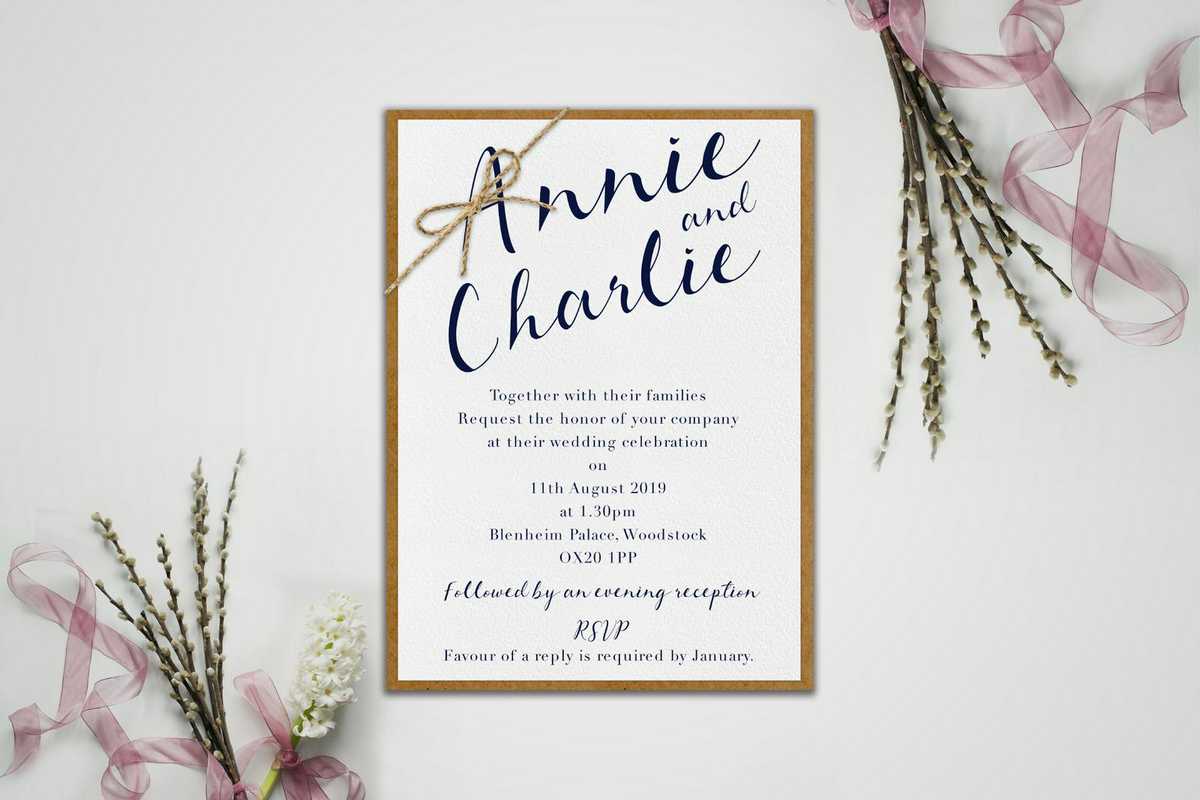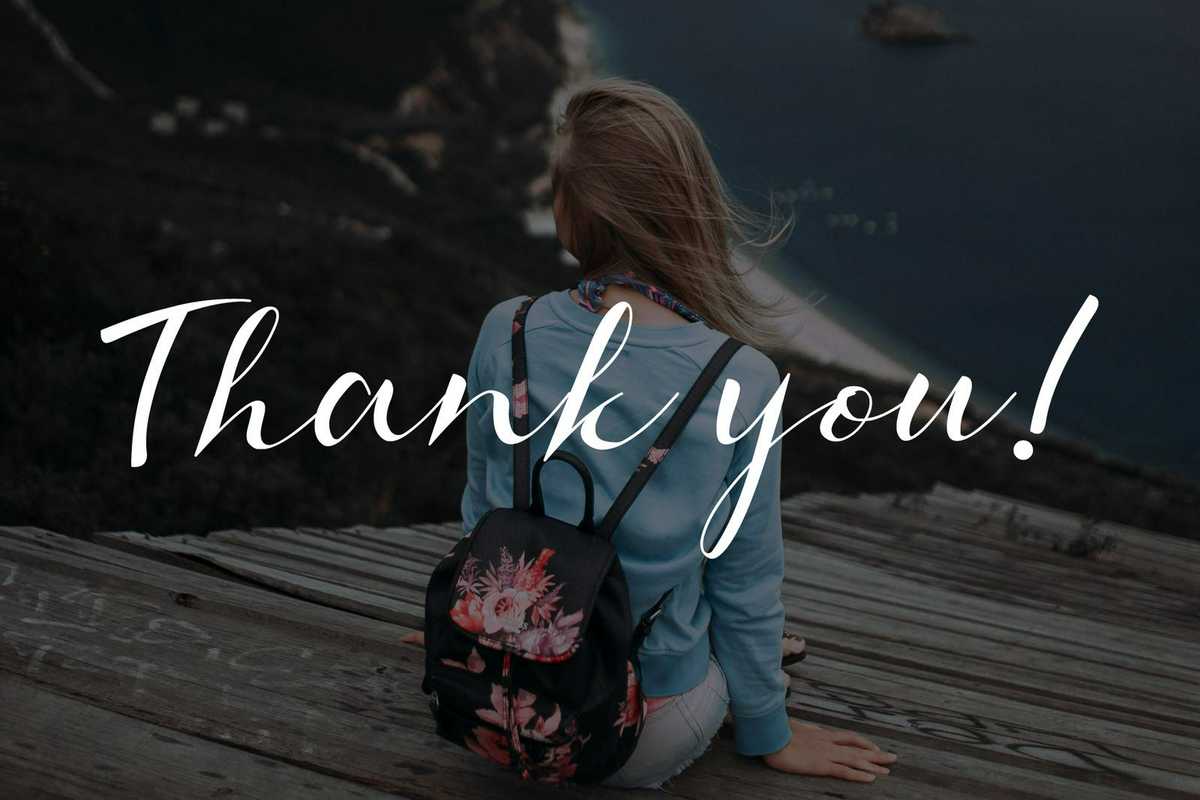
TaniyaFont非常适合摄影、水印、社交媒体、广告、徽标和品牌、邀请函、产品设计、标签、文具、婚礼设计、产品包装、特价商品或任何需要手工制作的物品。TaniyaFont非常适合摄影、水印、社交媒体、广告、徽标和品牌、邀请函、,产品设计、标签、文具、婚礼设计、产品包装、特殊物品或任何需要手工制作的物品。